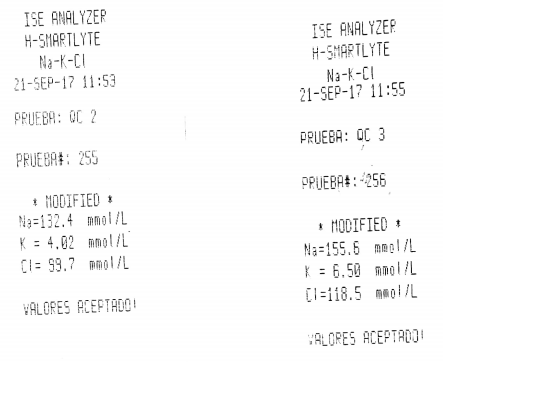
Foro de Tipografía Ayuda! Necesito saber que tipo de fuente es el 10.11.2017 a las 06:46 por vladyon · 2 comentarios Seguir este tema Dejar de seguir este tema 2 seguidores Buenas noches, soy nuevo. Pueden ayudarme, quisiera saber que tipo de fuente es la letra de la imagen. No la encuentro, es de una impresora térmica pero necesito imprimir con el mismo tipo de letra. Muchas gracias! Comentar Me gusta
La de tu muestra parece un poco más condensada, pero quizá podría servirte esta:
Fake Receipt: http://www.1001fonts.com/fake-receipt-font.html